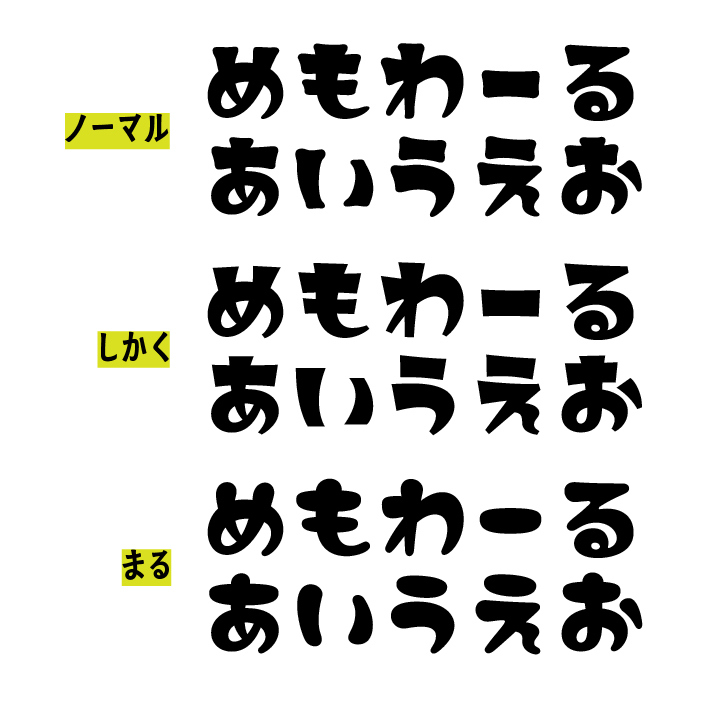
めもわーるは、ファンシーで可愛らしくインパクトのあるレトロポップなフォントです。Memoir(メモワール)はフランス語で記憶や思い出とのことです。
ひらがな・カタカナフォントなので、漢字は収録されていないですが、ひらがな・カタカナを使っているロゴやタイトルなどに取り入れると、可愛いロゴタイトルができます。
文章で使いたい場合は、他のフォントの漢字と混植文字として使うのもアリですね。配布サイトで混植文字のサンプルがあるのでぜひ参考にしてみてください。
「ノーマル」「しかく」「まる」のスタイルが3種類用意されています。
収録文字は、ひらがな・カタカナ・英数字が収録されています。